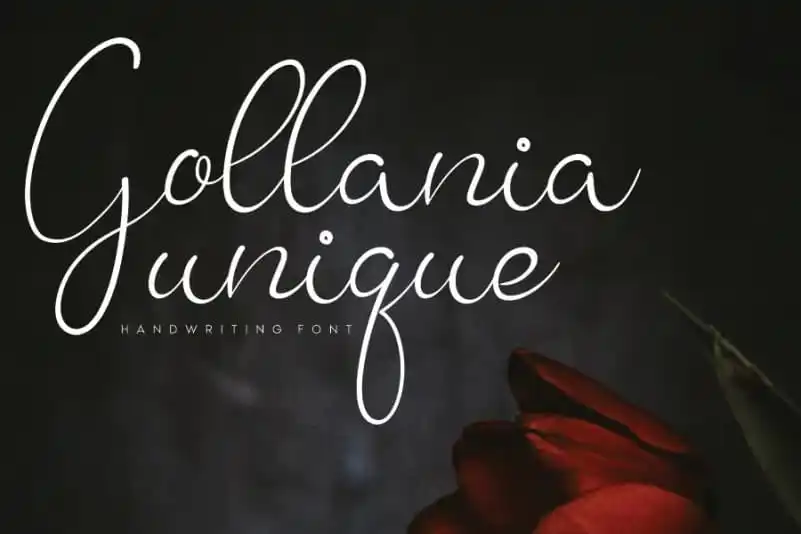
Gollania Handwritten Font – Fonte Grátis
Gollania Handwritten Font
A Gollania Handwritten Font é uma deliciosa tipografia escrita a mão que combina delicadeza e redondez. Inspirada na elegante calligrafia, ela transmite um estilo fluido e descontraído perfeito para festas especiais como casamentos e aniversários, cartões de cumprimento e muito mais. Este tipo de fonte traz uma sensação agradável e única aos seus projetos, tornando-o ideal para momentos significativos em que você deseja expressar emoção e personalidade com estilo refinado. Com Gollania Handwritten Font na sua coleção de fontes, não deixará dúvida sobre o seu comprometimento em usar algo único e especial para cada ocasião importante.